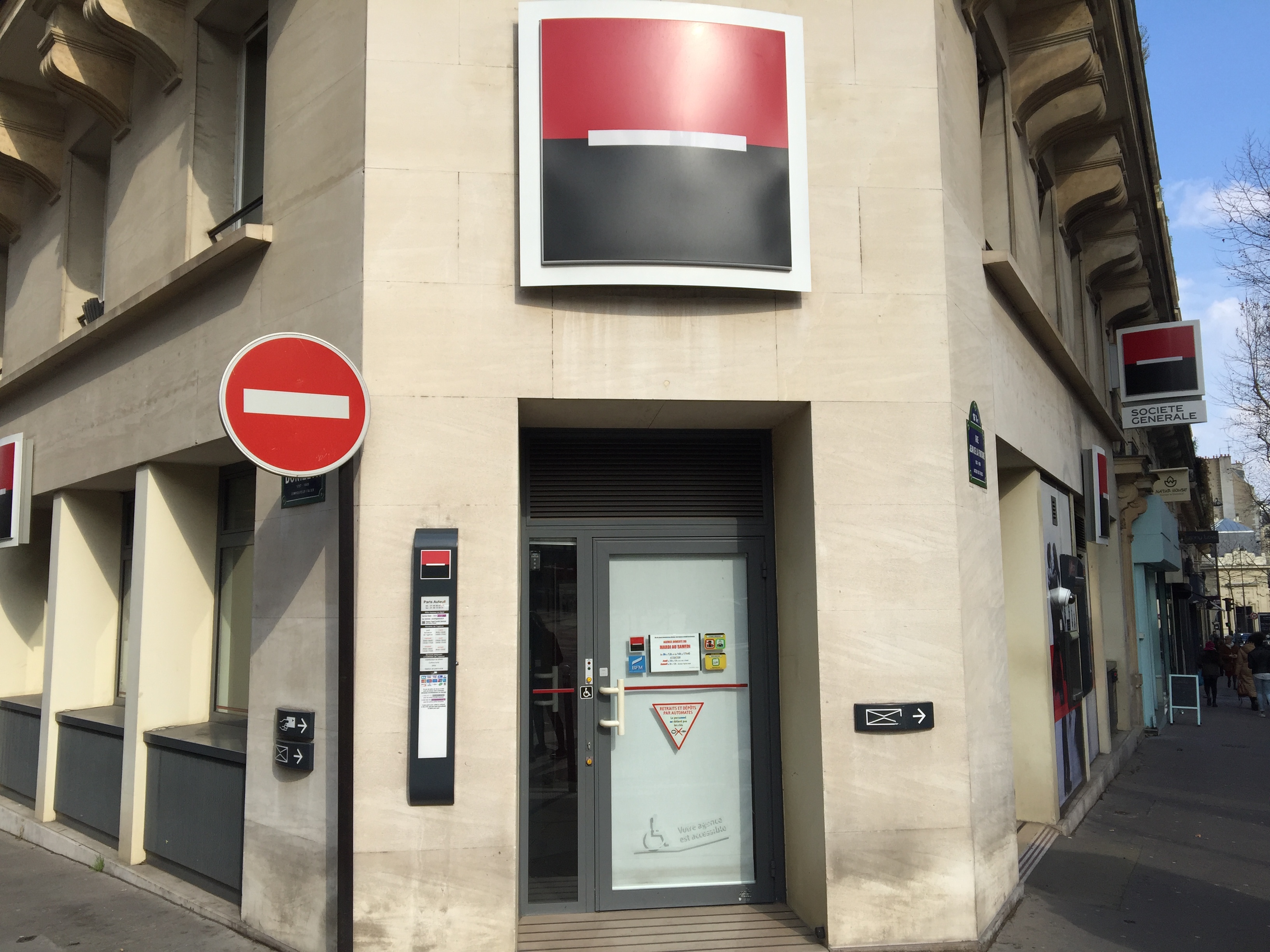
Logo Société Générale | Interdit d’entrer
Ou comment un établissement bancaire peut au travers de son logo dévoyer totalement sa mission. Je ne vais pas faire ici la liste de toutes les banques françaises ou étrangères. J’avais déjà consacré un article à la naissance de ce logo en 2006 je crois… (http://bit.ly/1LK90Ps) et Dominique Grosmangin qui avait dirigée la refonte du logotype et de la marque de la Banque, m’avait répondue ici (http://bit.ly/24tbhdj). Certains parmi vous comme Aaron Levin peuvent apporter leur témoignage avisé au déroulement de cette aventure professionnelle.
Mais voilà. Cela fait depuis longtemps que je voulais revenir sur la refonte de cette marque. Sur l’idée absolument sotte et grenue d’avoir sorti précisément le logotype du carré rouge et noir symboles de force et de germanisme. Vous vous souvenez qu’à l’époque j’avais cru que la création de cette nouvelle image était destinée à abandonner à terme le mot SOCIETE, sans accent comme le précise. Dominique Grosmangin) Pour ne garder uniquement que le substantif GENERAL. Au même moment il y avait des négociations entre la banque française et la banque Belge s’appelant La Générale, «négos» qui avaient échoués.
Mais voilà. Que se passe-t-il dix ans après mes premiers posts sur le sujet. La Banque Société Générale se trouve affublée d’un panneau de signalisation qui équivaut à un sens interdit. N’entrez surtout pas. Il n’y a personne ici pour vous parler, vous recevoir. D’ailleurs, l’opacité blindée de la porte d’entrée est là pour nous rappeler qu’il ne s’agit plus d’un lieu amical où l’on peut venir demander des conseils à des experts en placement, en finance ou tout simplement en crédits d’investissement. Circulez. Il n’y a rien à dire, ni à voir. Sens interdit. Allez donc vous connecter à notre banque en ligne et laissez nous robotiser, et licencier tout le personnel des guichets dont nous n’avons que faire. Votre argent travaille, pour nous. La Banque. Et cette porte que vous voyez là, et ce logo que vous discernez ici, sont là pour nous rappeler la mutation numérique du monde de la finance qui n’a plus que faire d’un commerce de proximité. Le Village est devenu Global grâce à McLuhan et la Société Générale vous dit « it’s closed » « do not enter ». It is not for You.
Alors qu’est-ce qu’un logo, qu’est-ce qu’une image de marque. À quoi ça sert ? À quoi ça a servi. Fédérer est sans doute le mot qui revenait le plus souvent dans la bouche des publicitaires et des designers. Fédérer les usagers-consommateurs autour de l’image d’une banque sympathique, accueillante et «près de chez vous»… Une image de marque servait à venir affirmer des valeurs, de service, de qualité et de confiance. Deux révolutions sont passés par là pour détruire des années de labeur des designers.
1— Les crises financières successives dont la dernière de 2008 a eu des conséquences dévastatrices sur la planète toute entière.
2— La digitalisation ou numérisation, à marche forcée des établissements financiers. Plus de bourse, plus de salles de marché, plus d’agences, plus de conseillers. Des algorithmes et du Big Data. Et des Flux à Très Haute Fréquence. La Banque a cessé d’être ce lieu magique où l’on pouvait encore négocier son avenir et convaincre un être humain du bien fondé de ses projets.
Sens Interdit. N’entrez pas dans cette Banque, car elle n’existe plus. Ce coin de rue, ce panneau sens interdit, ce symbole Rouge et Noir traversé horizontalement par un trait blanc signifie sans conteste une image négative, celui d’un passage interdit, d’un lieu interdit, d’une voie interdite, d’un SENS interdit.
Est-ce là un symptôme ou un Saint-Homme comme dirait certains de mes connaissances, en tous cas voici venir un monde merveilleux où il va être essentiel de trouver du sens.